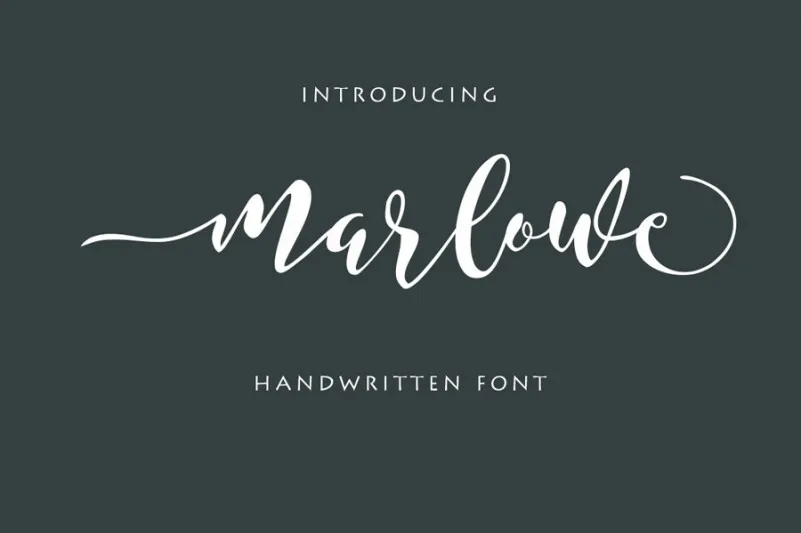
A Marlowe Script Font é uma criação inovadora que transmite um toque autêntico de arte manual na sua próxima peça de design. Inspirada no estilo delicado e artesanal do calligrafia, esta fonte se destaca por oferecer linhas fluidas e detalhes finos, sem deixar de ser moderna e elegante para atender ao público exigente e criativo atual. Seja você um designer gráfico profissional ou iniciante, a Marlowe traz uma experiência única que vai revolucionar seu estilo de trabalho. Suas linhas curvas leves e o detalhe dos traços proporcionam profundidade e sensibilidade em qualquer projeto. Perfect para adicionar um toque distintivo à sua próxima obra, é a escolha perfeita para quem busca mais do que apenas uma fonte; eles procuram uma experiência única que transborda personalidade e arte manual. Marlowe atinge o equilíbrio ideal entre modernidade e elegância, oferecendo um meio de expressar-se de maneira autêntica através da tipografia. Como parte da nossa coleção de fontes Script, a Marlowe é perfeita para qualquer projeto que busque uma abordagem criativa e inovadora. Ela não apenas adicionará personalidade ao seu design; ela redefinirá completamente como você trabalha.